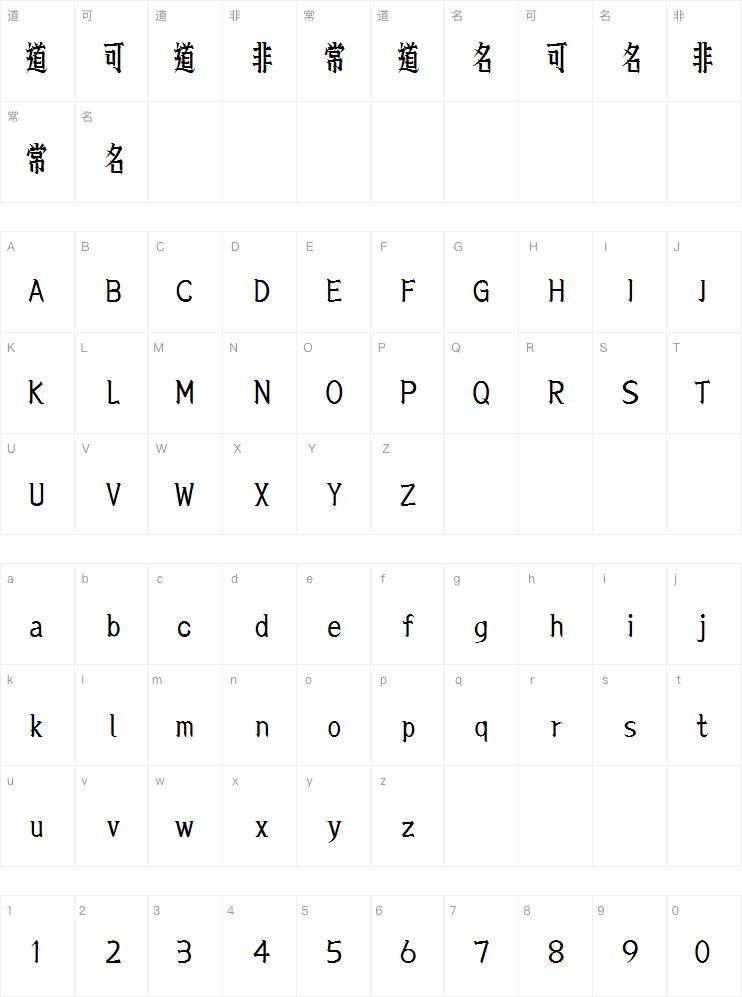
上首寒枝体,简体中文约6763字。名字取自于 苏轼的“拣尽寒枝不肯栖”。该字字型劲瘦,自带清冽孤傲之感又给人留有一种冷峻雅致的印象。字体笔画似孤枝挺立寒风,尽显孤高风骨,融合了宋体的衬线雅致与手写的自然随性的笔意,使字型文雅而不刻板兼具了古朴与灵动,富有文人气息。整套字体风格统一、特点一致,字体个性鲜明,具有艺术感,适用于搭配标志、广告标语、商业广告、海报字体等高端属性。